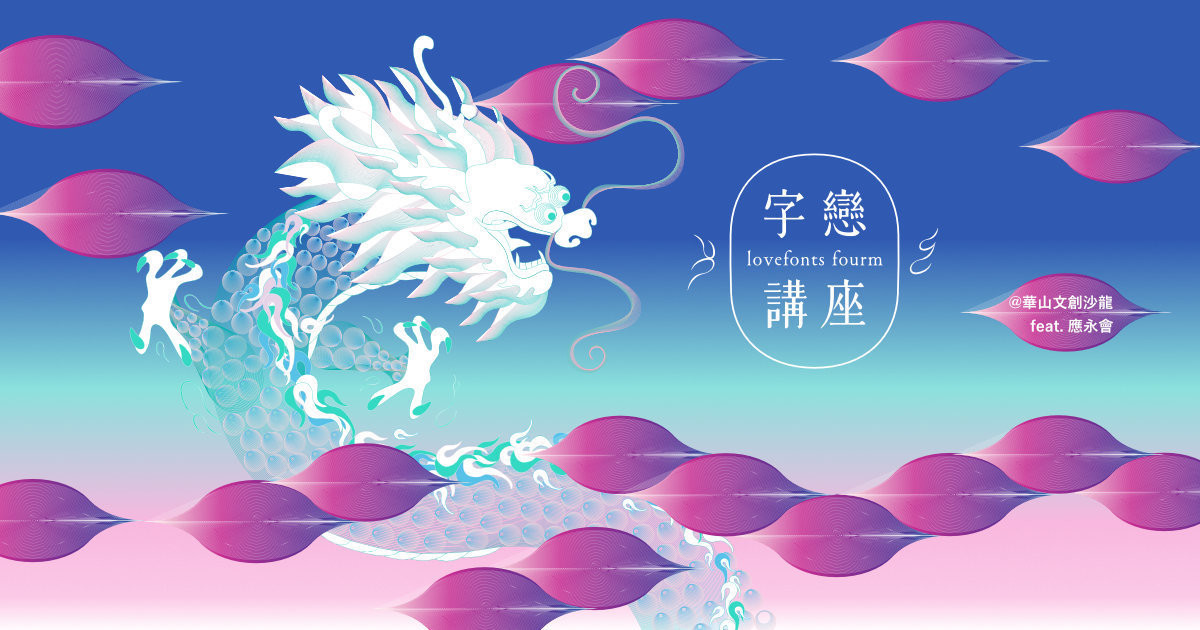
字戀講座是
由 justfont 主辦、籌劃的全新免費字型講座,
除了希望能推廣字型相關知識外,
也希望讓大家更深入瞭解字型設計的文化、歷史、技術、哲學⋯⋯
每次講座前半場,都會帶給大家台灣民眾必修的基本的字型知識,
也會在後半場依照時事、互動調查需求來規劃有趣的次領域主題,
希望能用輕鬆好玩的方式,讓大家更親近這個與我們息息相關的領域。
「為什麼康熙字典體不是一套好的「字型」?」「明體是怎樣來的?沒有字型的年代怎麼排印?」「要怎麼駕馭一個復古的感覺?」「復古跟新潮都很會?安安你字型系?」
第二場主題:字型復古夜,復古新潮,都很會
人情淡薄的年代,復古字體崛起,希望帶回有機的情感。
從古籍精華而來,字型要怎麼做,才能保留古典精神,又能為現代設計所用?
康熙字典體帶來了視覺風景的衝擊,但為什麼有些設計師要抵制它?
使用古典的字型可能不是怎樣都可以。那我們該怎麼辦?
★ 由 jf 金萱設計師群主講
★ 上半場講題講解字型的基礎知識
★ 從身邊出發,深入淺出的講座主題
特別來賓:應永會
平面設計師,業餘時間做字,憑著恆心毅力,十年之間,製作了「汲古書體」、「浙江民間書刻」體等從古籍得到靈感的字型。本著字娛字樂的心情做字,志向卻放得很長遠:希望這些帶有古典精神的字型,能夠為現代中文設計帶來新的面貌。本次登台,將會與我們分享他製作古籍書體的心路歷程。